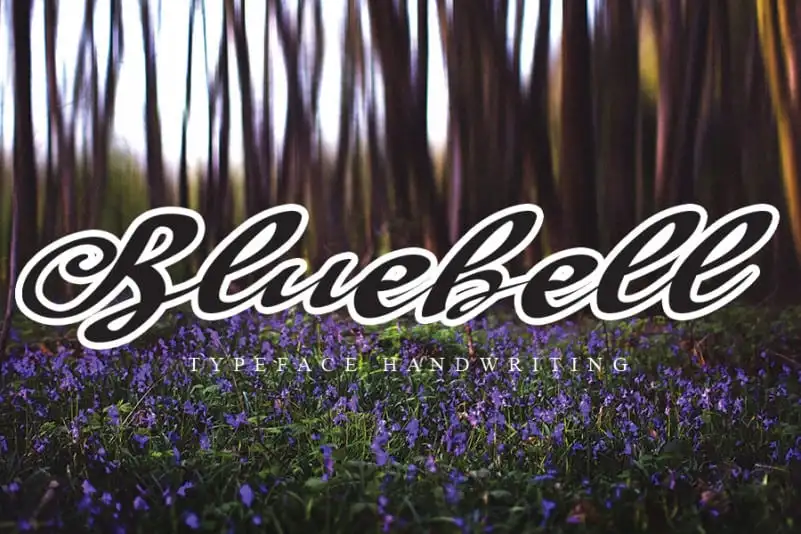
Bluebell Script Font – Download Grátis
A Bluebell Font é uma tipografia escrita à mão com influências clássicas do traçado, que mantém sua elegância enquanto parece contemporânea e fresca. Este estilo elegante irá destacar-se perfeitamente nos convites de casamento, postagens nas redes sociais, logotipos, marcação e muito mais. É um verdadeiro prazer experimentar a versatilidade desta fonte em designs variados e complexos, enquanto aprecia sua sofisticação única. Seja você designer, publicitário ou amante de design gráfico, a Bluebell Font oferece uma solução perfeita para expressar seu trabalho de maneira criativa e impecável.